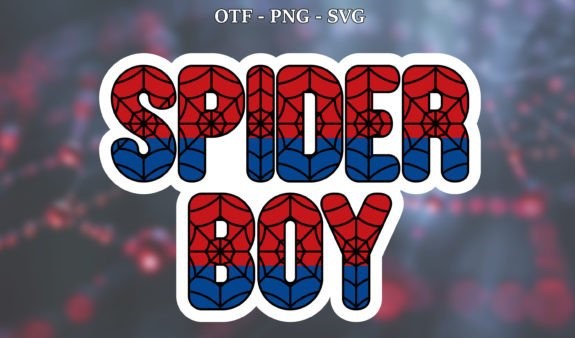
Spider Boy Font
Spider Boy Font – الخط المثالي لتصاميم إبداعية وجذابة
أضف لمسة من الجرأة والإثارة إلى تصاميمك مع Spider Boy Font، الخط العصري المستوحى من أجواء الكوميكس والأبطال الخارقين! يتميز هذا الخط بتصميم فريد يجمع بين الحدة والانسيابية، مما يجعله خيارًا مثاليًا للعناوين البارزة، الشعارات، التصميمات الجرافيكية، وأغلفة الكتب والألعاب.
✅ تصميم احترافي مستوحى من عالم الكوميكس والأبطال الخارقين
✅ يدعم الحروف الكبيرة والصغيرة مع تفاصيل ديناميكية مذهلة
✅ مثالي للعناوين، الشعارات، الإعلانات، والمحتوى الإبداعي
أطلق العنان لإبداعك وأضف لمسة من الإثارة إلى مشاريعك مع Spider Boy Font! ????✨